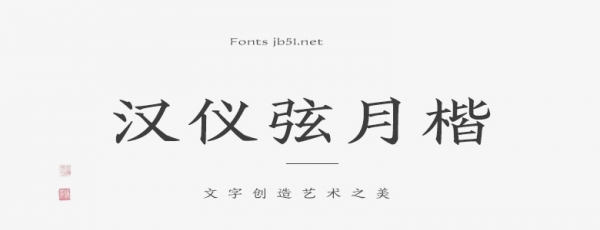
漢儀弦月楷簡(jiǎn)字體融合了傳統(tǒng)楷書和現(xiàn)代設(shè)計(jì)的特點(diǎn),使其既具有傳統(tǒng)字體的古典美感,又具有現(xiàn)代字體的清新簡(jiǎn)潔之美。它的設(shè)計(jì)風(fēng)格兼具傳統(tǒng)與時(shí)尚,給人以文化底蘊(yùn)深厚、雅致與高端的感覺。